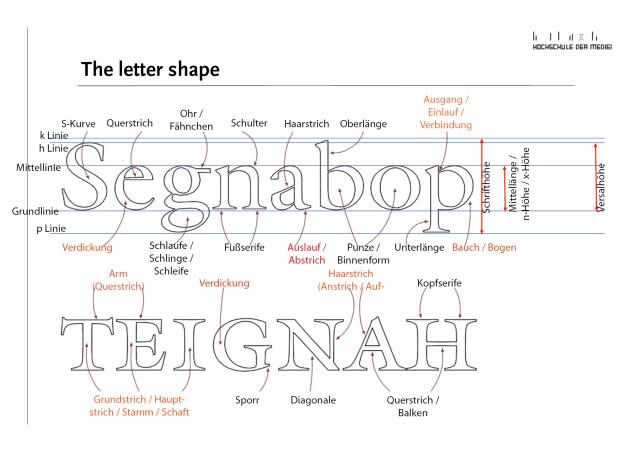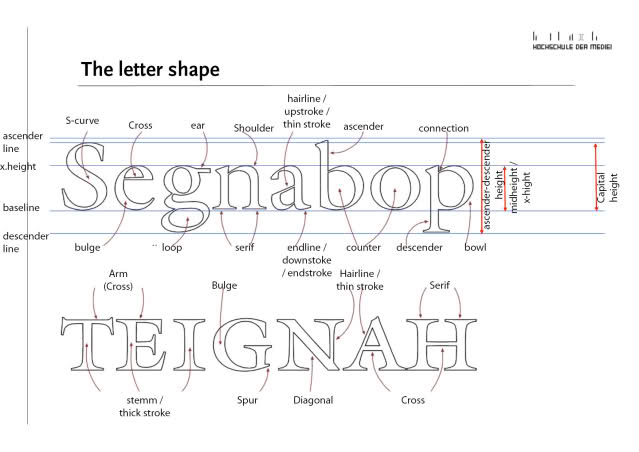
Typografische Begriffe: Benamung Bestandteile Buchstaben
ich muss für den Typografie-Kurs in der Uni die Teile der Buchstaben beschrifen, auf Deutsch und English. Ich hab leider noch nicht so viel Erfahrung in Typografie und hab versucht mit Hilfe von Fachliteratur die richtigen Bezeichnungen zu finden. Unten seht ihr mein Resultat. Könnt ihr mal schauen, ob die Begriffe so stimmen? Vor allem bei den rot markierten und bei den englischen Begriffen war ich mir unsicher.
Das ist jetzt nicht komplett, aber mal so ein paar Bemerkungen. Allerdings glaube ich, dass sich die Nomenklatur auch von Schule zu Schule und von Region zu Region unterscheiden kann. Also vielleicht nicht alles komplett kritiklos übernehmen :)
Deutsch:
– Ich verstehe den Unterschied zwischen «k Linie» und «h Linie» nicht (und da gehörte auch ein Bindestrich dazwischen, wie auch bei der «p Linie»). Ich dachte erst, es handle sich um die Versalhöhe vs. die h-Höhe, scheint aber nicht so zu sein? Sind «k»s nicht gleich hoch wie «h»s? :twisted:
(Und im Englischen steht ja dann auch nur noch «ascender line»…)
Englisch:
– «x height» ist m.E. genaugenommen falsch. Die Linie an sich wird mit «x-line» bezeichnet, die «x-height» ist der Abstand zwischen Grundlinie und x-Linie; die Höhe des «x» eben.
– T, E, I: «stem» schreibt man mit einem «m»,
– T, E, I, A, H, e: für die Querbalken ist m.E. «crossbar» am üblichsten. «Cross» heißt Kreuz; das Wort kenne ich persönlich nicht aus dem Kontext. «Arm» kenne ich übrigens eher als die obere (aufsteigende) Diagonale beim «K» (und «k»).
– Ein gutes Wort für den Abschluss – das, was Du beim «a» «endline, downstroke / endstroke» genannt hast, ist «terminal». (Dt. auch «Endung», wie z.B. in «Kugelendung» / «ball terminal» oder «Tropfenendung» / «teardrop terminal».)
– p: Statt «connection» würd ich eher «join» sagen.
Hallo Nina,
vielen vielen Dank für deine Hilfe!!! Jetzt bin ich schon wieder ein Stück weiter. Hier kurz ein paar Anmerkungen:
"Allerdings glaube ich, dass sich die Nomenklatur auch von Schule zu Schule und von Region zu Region unterscheiden kann. Also vielleicht nicht alles komplett kritiklos übernehmen"
Ja das hab ich auch schon bemerkt, in vielen Foren / Internetseiten / Fachbüchern werden ein und dieselben Dinge komplett unterschiedlich benannt.
– Ich verstehe den Unterschied zwischen «k Linie» und «h Linie» nicht [...] Ich dachte erst, es handle sich um die Versalhöhe vs. die h-Höhe, scheint aber nicht so zu sein? Sind «k»s nicht gleich hoch wie «h»s? (Und im Englischen steht ja dann auch nur noch «ascender line»…)
Das Problem war, dass ich in Englischen Büchern für die oberste Linie nur "Ascender line" gefunden habe, in Deutschen Büchern wurde aber teils zwischen h- und k-linie unterschieden. Die obere Linie soll die k-linie sein und die untere Linie die h-linie. Leider habe ich keine Erklärung dafür gefunden. Mir ist der Unterschied auch nicht klar.
Nur geil! :hammer:
Puncto h und k: Ich glaube, da liegt ein Missverständnis vor mit Versalhöhe und Oberlänge (siehe auch die roten Pfeile). Wobei das allerdings wieder nicht recht zu den Buchstabenformen passt…
Die obere Linie soll die k-linie sein und die untere Linie die h-linie. Leider habe ich keine Erklärung dafür gefunden. Mir ist der Unterschied auch nicht klar.
Gemeint ist wohl die H-Linie (Versalhöhe).
Und der „Stachel“ am G heißt Sporn, nicht Sporr.
Ich hab mal ne Frage zum Thema. Man spricht ja bei bestimmten optischen Korrekturen von over- beziehungsweise undershoot. Gibt es da einen deutschen Fachausdruck für?
Ich habe dafür die Begriffe »kleiner Überhang« (oben) und »unterer Überhang«.